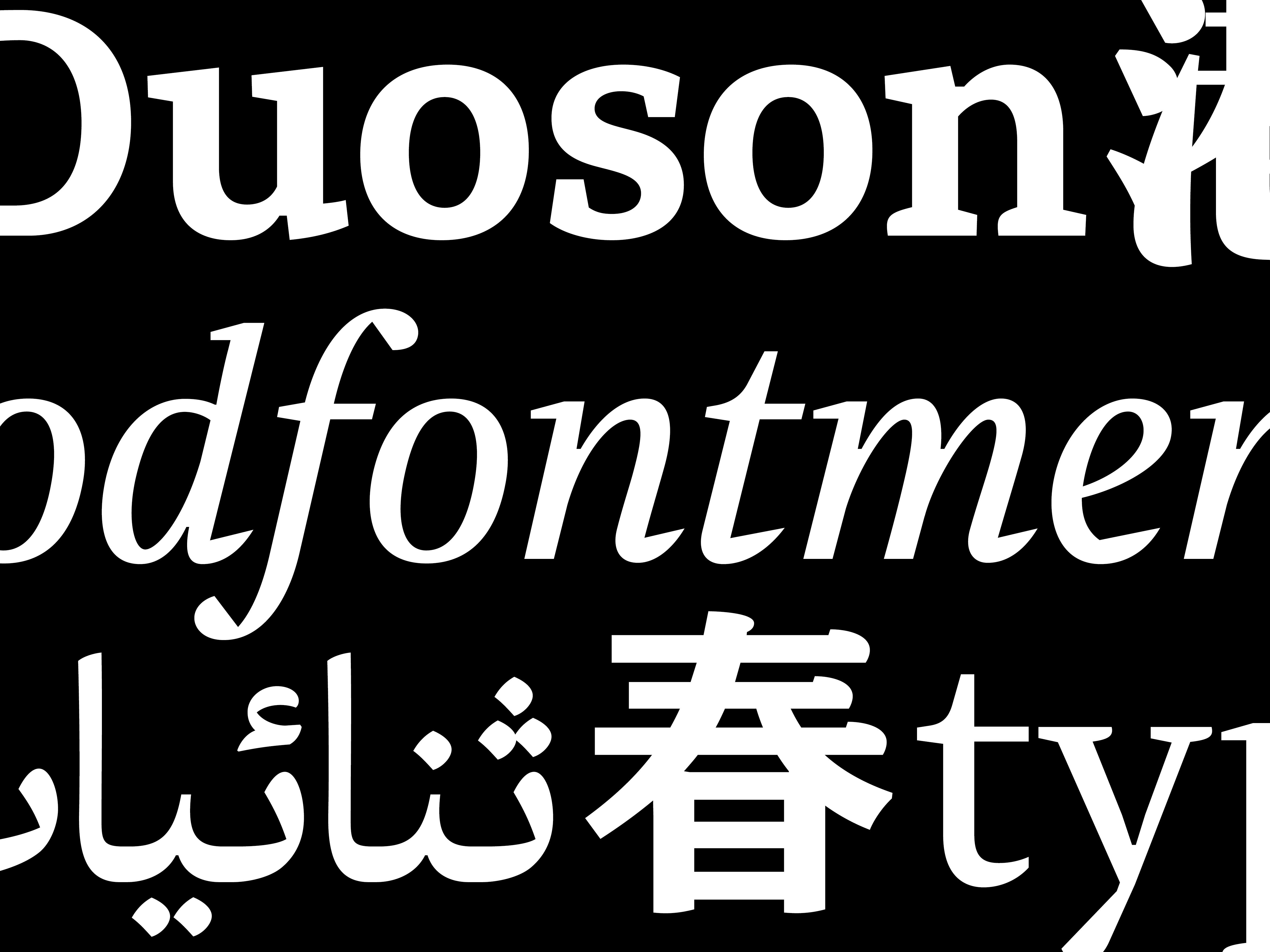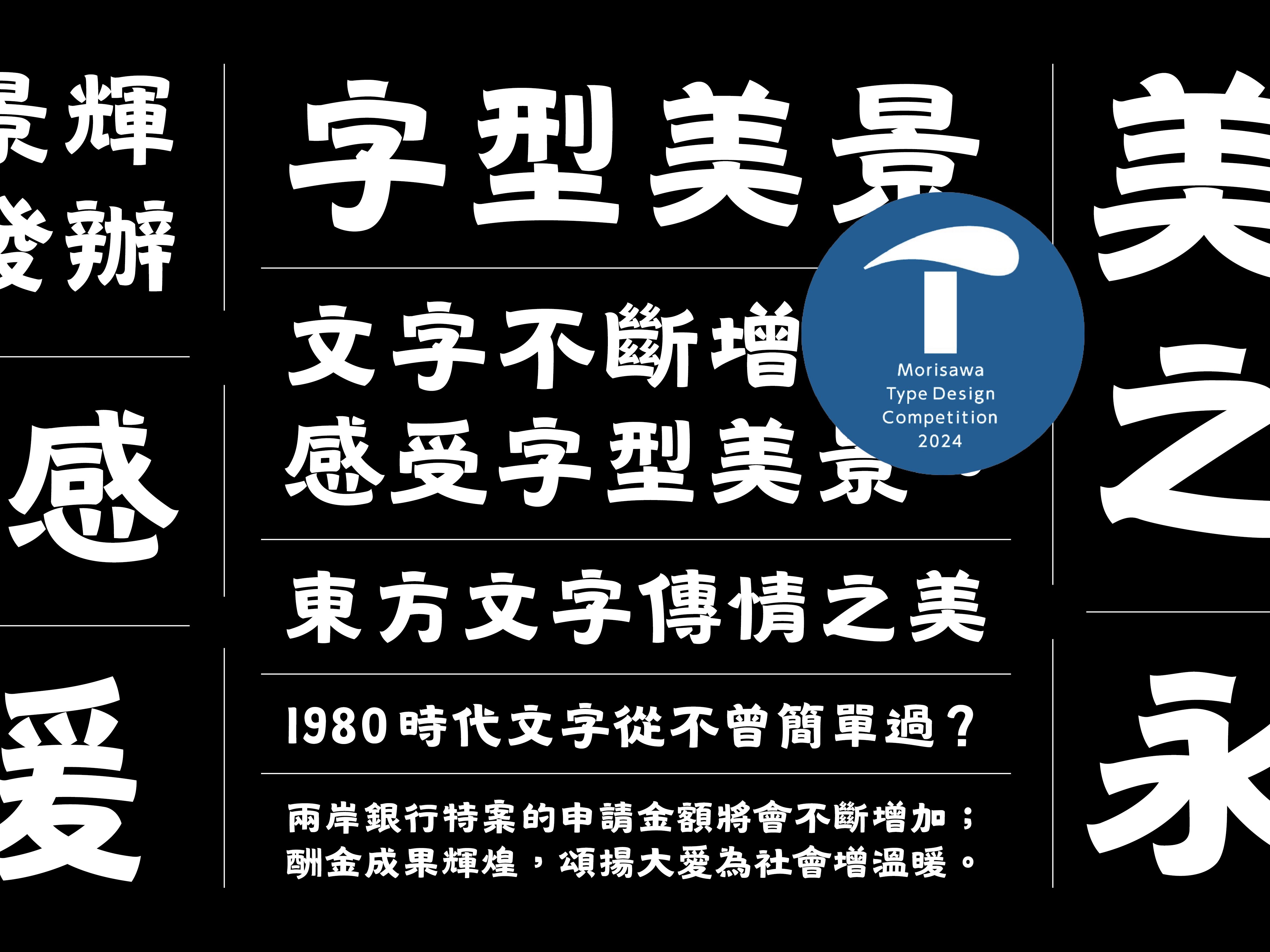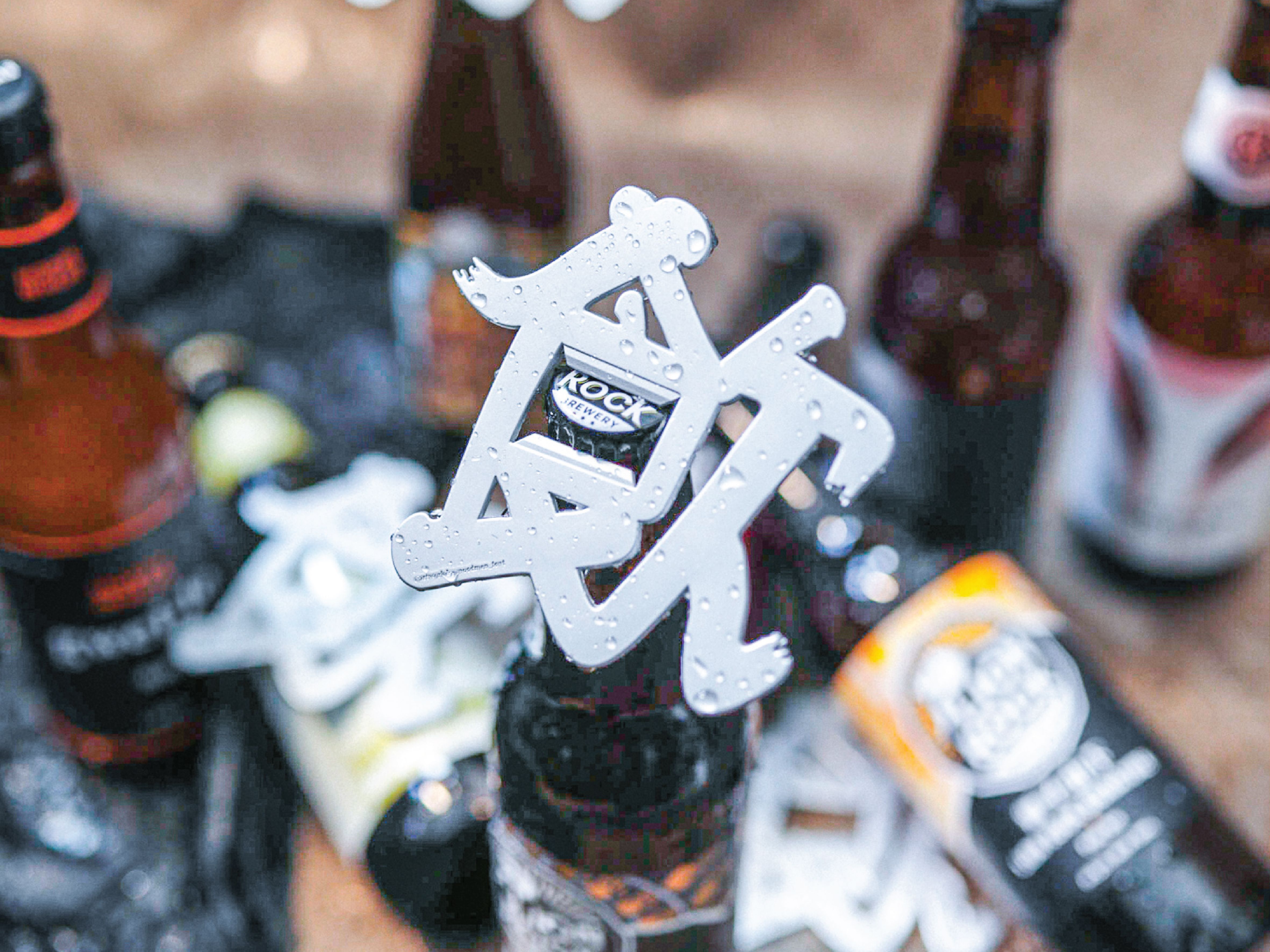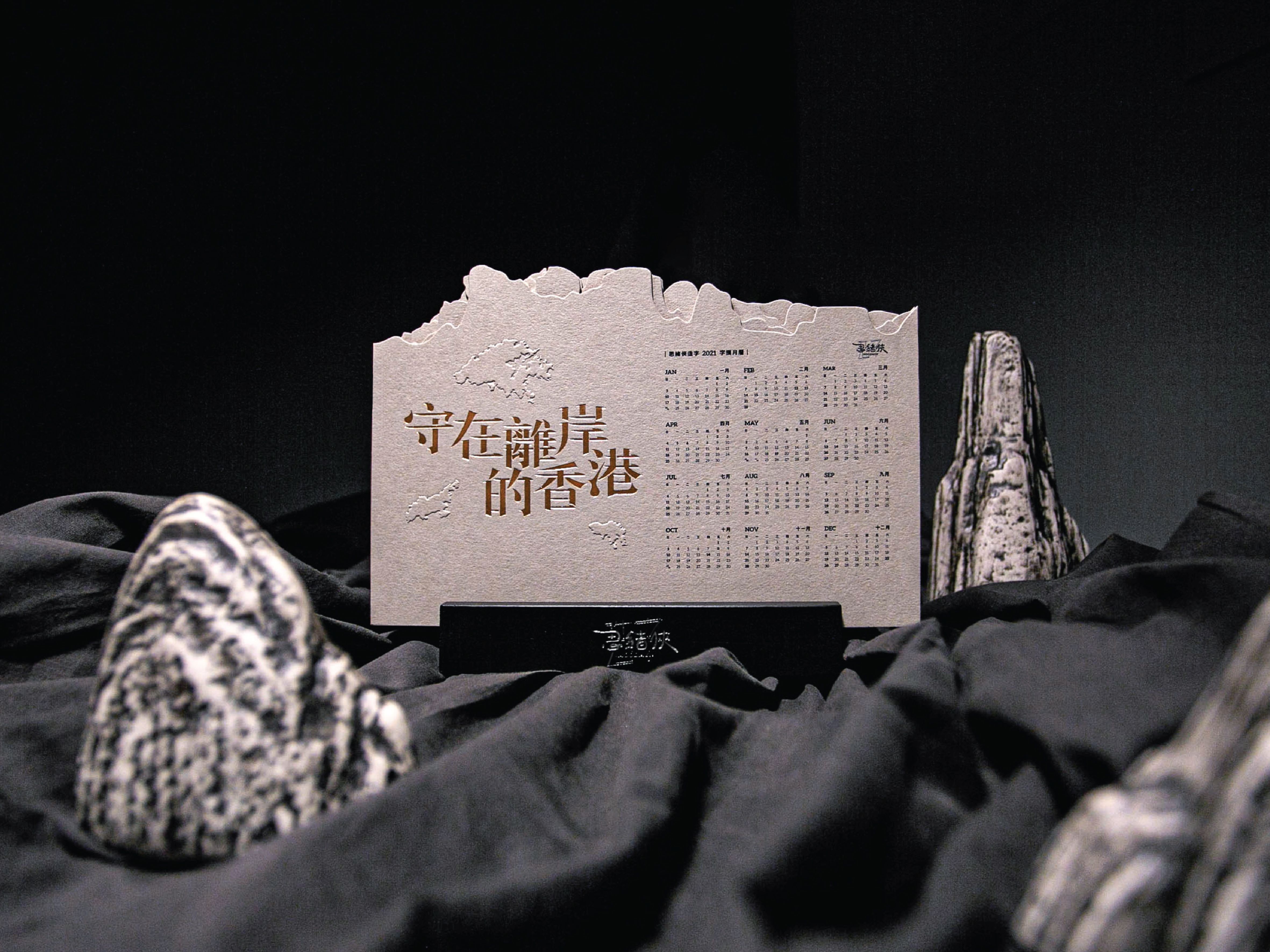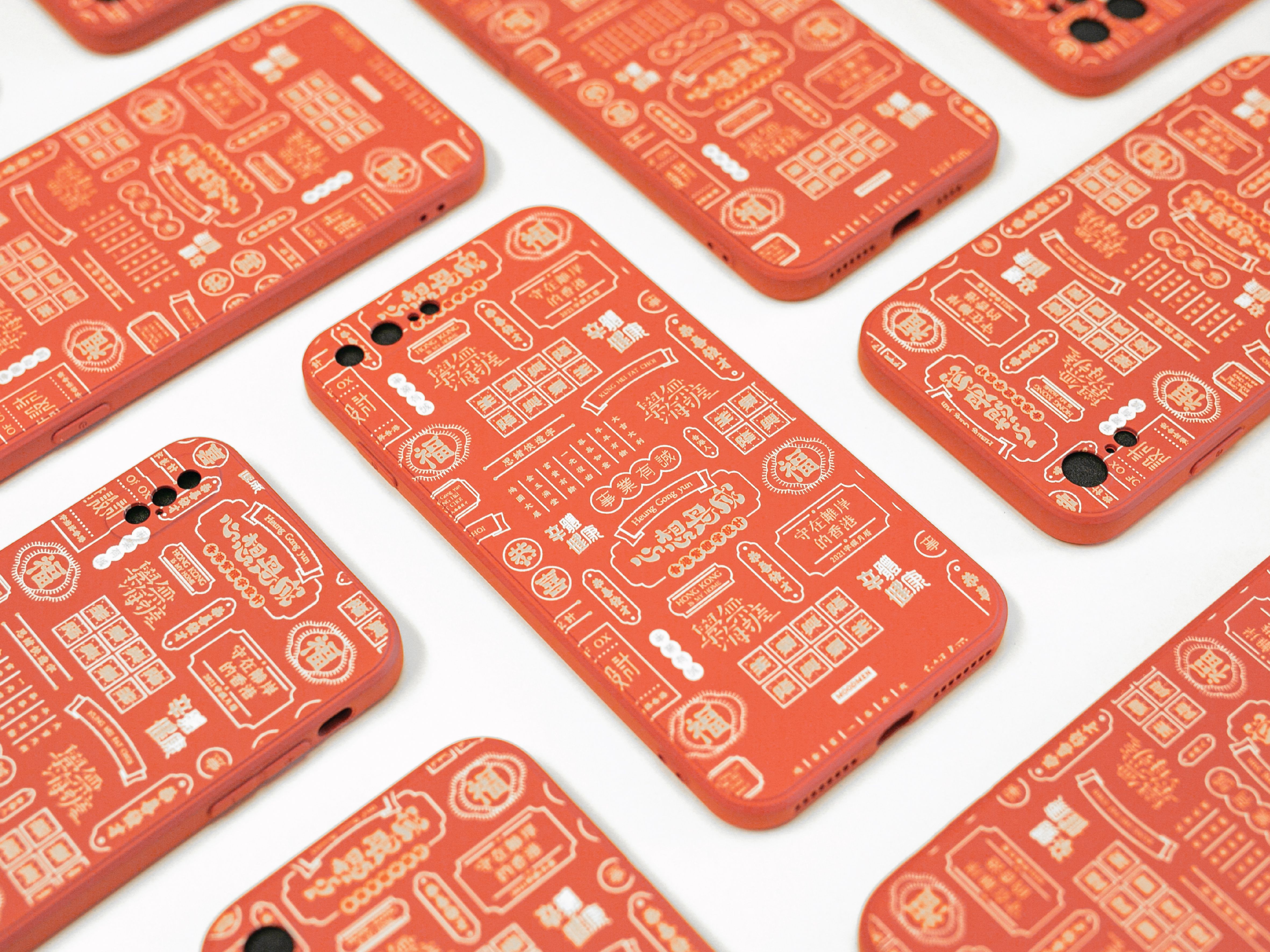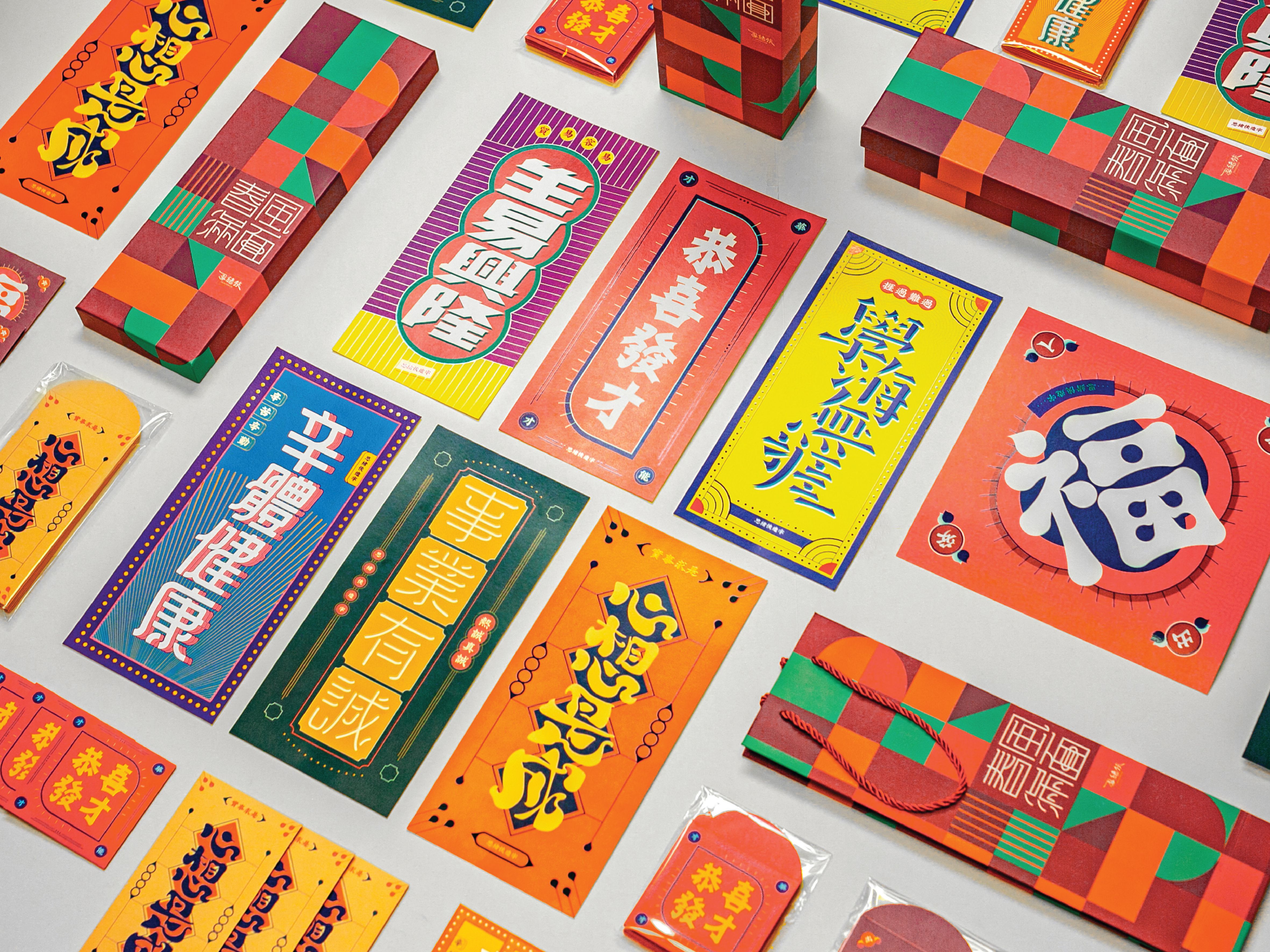
陳靖軒 Roy Chan
字體設計師及顧問
字體不只是設計,多數人看見的是文字的外框線,我更在意的是字體構成背後的系統。 ”
陳靖軒Roy Chan是蒙納香港的高級創意字體顧問。
他畢業於廣告設計,其後對廣告中的標題字產生興趣,成立工作室製作以藝術字為主題的商品,其後完成兩套繁體中文的字體開發。為深化字體技藝,他其後到英國雷丁大學修讀字體設計碩士課程,畢業論文研究19世紀初製成的中文活字【香港字】的數據分析與復刻概論。
他曾獲 2025 年 DFA 香港青年設計才俊獎,2024 年森澤字體設計競賽佳作獎,亦是國際字體協會(ATypI)的地區和社群代表(香港),每年為該區撰寫字體設計趨勢報告。